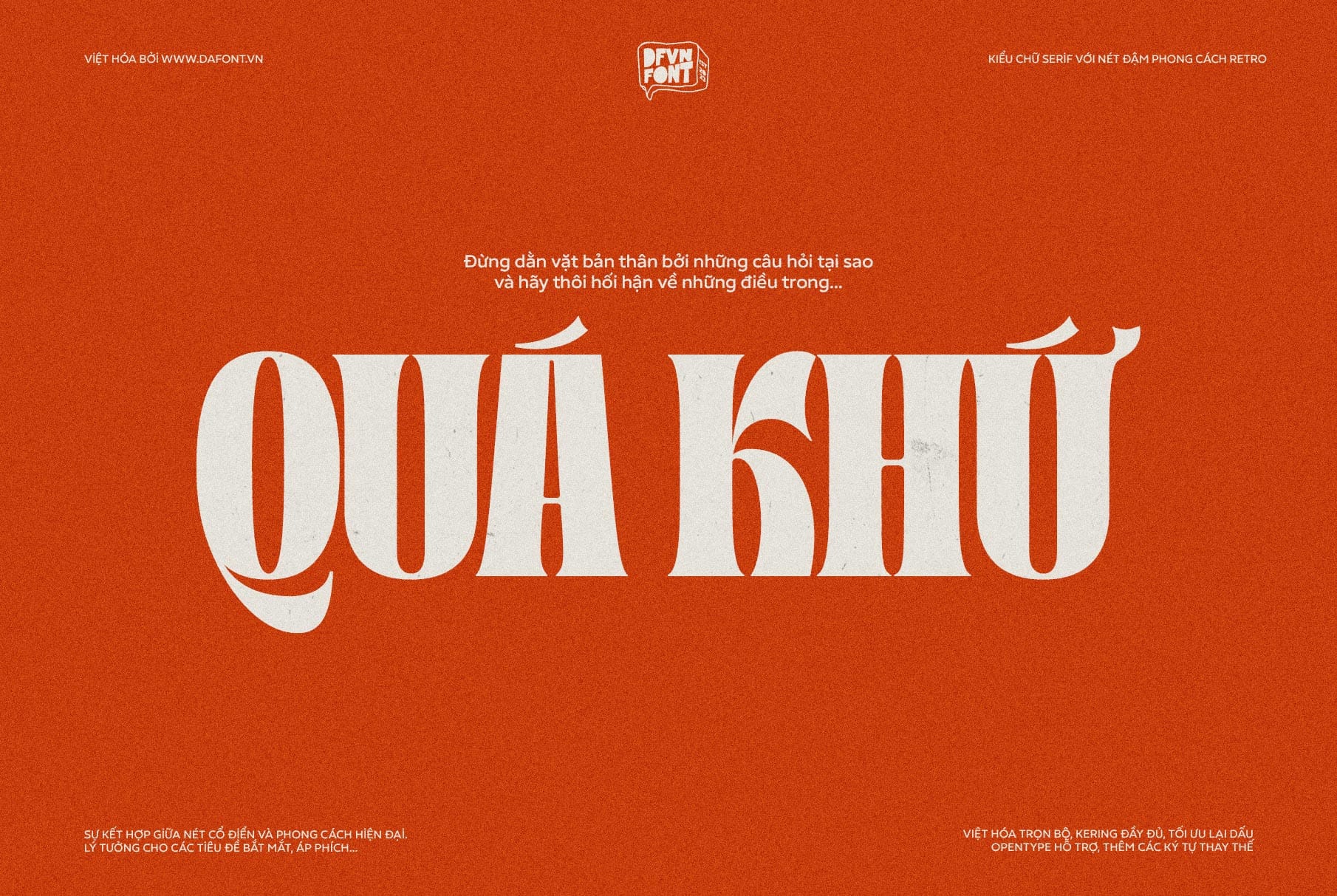
Nếu bạn đang tìm kiếm một kiểu chữ đậm chất retro nhưng vẫn giữ được nét hiện đại, TAN – BRISTOL AVENUE chính là sự lựa chọn hoàn hảo. Đây là một phông chữ không chỉ tạo điểm nhấn nổi bật mà còn mang lại cảm giác hoài cổ tinh tế, phù hợp cho mọi dự án thiết kế.
TAN – BRISTOL AVENUE là một kiểu chữ đậm chất retro với nhiều điểm nổi bật đáng chú ý:
- Thiết kế góc cạnh và mạnh mẽ: Các nét chữ được thiết kế với đường nét sắc sảo, góc cạnh, tạo nên cảm giác nổi bật. Phong cách này vừa mang lại cảm giác hoài cổ vừa thể hiện sự cá tính hiện đại.
- Tính ứng dụng linh hoạt: TAN – BRISTOL AVENUE có thể sử dụng cho nhiều loại thiết kế khác nhau, từ logo, poster, bìa sách đến các dự án truyền thông số. Nó phù hợp cho cả các thiết kế cổ điển lẫn hiện đại, tạo nên sự đa năng vượt trội.
- Phong cách retro độc đáo: Lấy cảm hứng từ phong cách retro, kiểu chữ này gợi nhớ đến những thập niên trước, với một sự tinh tế riêng biệt giúp tạo điểm nhấn cho bất kỳ thiết kế nào.
- Kiểu chữ đậm, thu hút sự chú ý: Với độ dày nổi bật làm nổi bật nội dung một cách tự nhiên, thu hút ánh nhìn ngay lập tức, đặc biệt phù hợp cho tiêu đề hoặc các điểm nhấn chính.
- Phong cách tối giản nhưng đầy cuốn hút: Tuy không quá cầu kỳ, nhưng sự cân đối trong thiết kế giúp TAN – BRISTOL AVENUE dễ dàng gây ấn tượng mà không cần quá phô trương.
TAN – BRISTOL AVENUE: Sức hút từ nét chữ góc cạnh
TAN – BRISTOL AVENUE là một kiểu chữ đậm (bold) được thiết kế để tái hiện phong cách retro của thập niên trước, đồng thời mang đến hơi thở của thời đại mới. Sự tinh tế trong từng đường nét khiến font chữ này vừa phù hợp với các thiết kế thương hiệu, logo, poster, banner, thumbnail video, bìa sách, tạp chí, các ấn phẩm truyền thông xã hội.
Các nét chữ của TAN BRISTOL AVENUE được thiết kế với đường nét góc cạnh độc đáo, tạo cảm giác mạnh mẽ và sắc sảo. Chính sự táo bạo này mang đến cho kiểu chữ vẻ ngoài ấn tượng, giúp nội dung thiết kế trở nên nổi bật và đậm chất cá tính. Những đường nét góc cạnh không chỉ gợi lên cảm giác hoài cổ mà còn thổi vào đó hơi thở hiện đại, khiến TAN BRISTOL AVENUE trở thành lựa chọn lý tưởng cho các thiết kế mang phong cách thời thượng.
TAN – BRISTOL AVENUE: Kiểu chữ đậm chất retro
TAN – BRISTOL AVENUE không chỉ là một font chữ, mà còn là một cách để bạn kể câu chuyện của mình một cách ấn tượng và khác biệt. Hãy để kiểu chữ này biến những ý tưởng của bạn thành tác phẩm nghệ thuật đầy cảm hứng!
Font được Việt hóa đầy đủ, các dấu đã được tối ưu lại để phù hợp hơn với các ký tự góc cạnh của font. Ngoài ra, kerning lại tất cả các ký tự bởi font gốc chưa được kerning đối với các ký tự tiếng Việt.